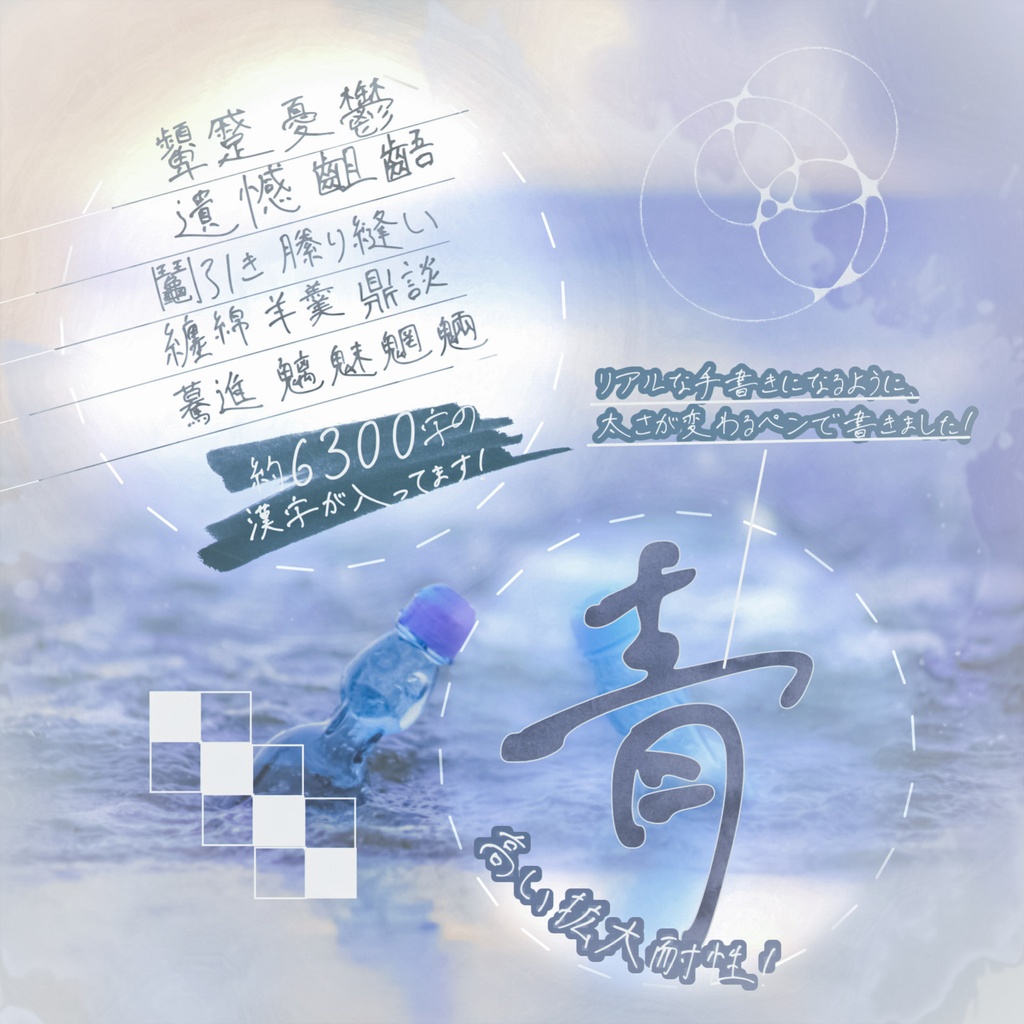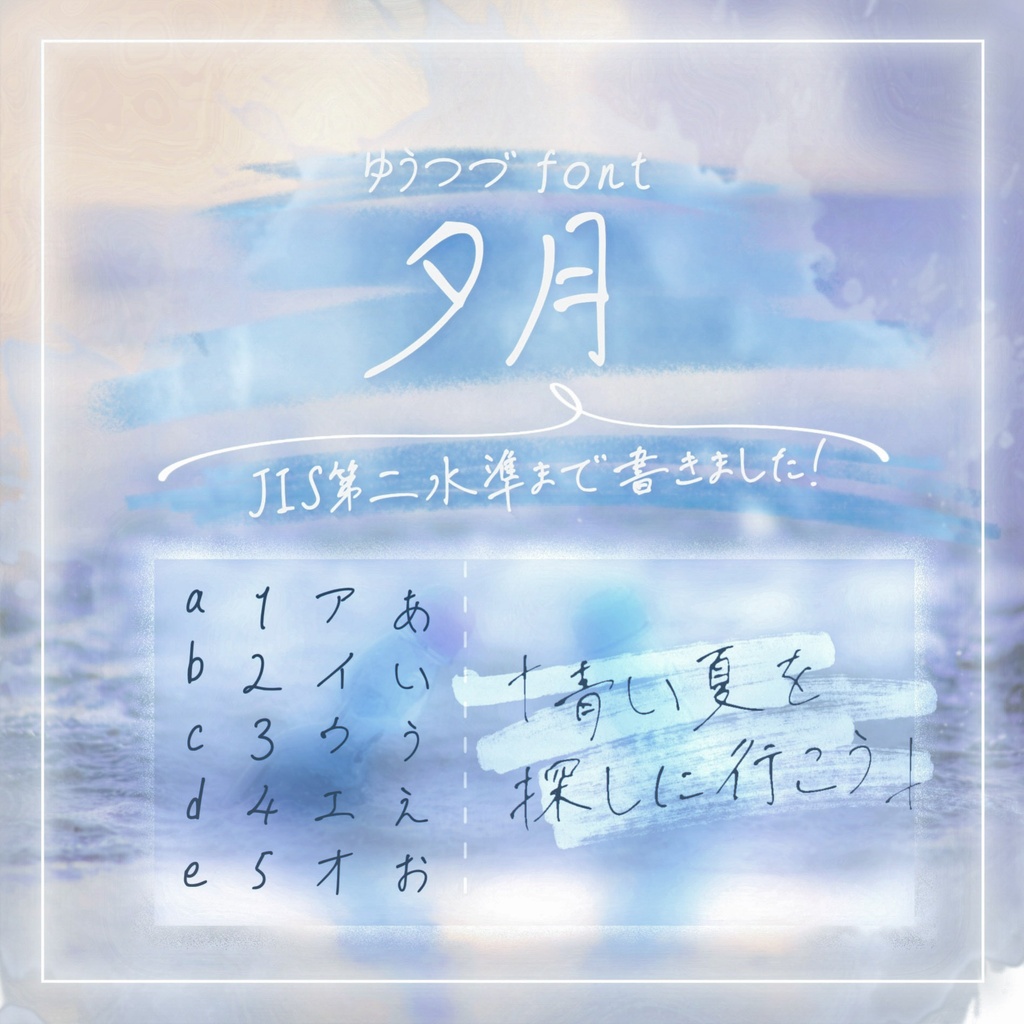
【無料版あり】手書き風日本語フォント「夕月(Yutsudu)」 oso
────────────── 🌙 1000スキ!&一周年記念 ────────────── いつも「夕月」を見つけてくださり、ありがとうございます。 おかげさまで 1000スキ!を突破しました 🎉 そして、公開から一周年を迎えることもできました。 夏の終わりに、ぜひ「夕月」をお手に取ってみてください。🌿 ■ 紹介 JIS第二水準まで対応した、爽やかで柔らかい手書き風日本語フォントです! 日常生活で用いる漢字はもちろん、難解な語句、地名にも対応しております。 縦書きにも対応しています。 人間味あふれる字形で、どこか儚く、淡く、青々しい情景と相性抜群です! 打つだけで演出できる「エモさ」を、ぜひお試しください。 ■ 特徴 ・高い拡大耐性 ・個性的でありながら、可読性を損なわない字形 ・線の太さが連続的に、かつ滑らかに変化 ・豊富な文字収録数 ・縦書きに対応 ■ ご紹介いただいたサイト ・いいフォント 様 https://goodfreefonts.com/8397/ ・フォントラボ 様 https://font-labo.com/yutsudu-font/ ・日本語フリーフォント 様 https://ffont.jp/yutsudu/ ・coliss 様 https://coliss.com/articles/freebies/japanese-free-fonts.html#h209 ■ おかげさまで 累計ダウンロード数が7000を突破しました! ご購入くださった皆さまはもちろん、SNSやブログなどで紹介してくださった皆さまにも深く感謝申し上げます。 ■ 注意・留意 ・カーニングを推奨します。 ・有料版をご購入される前に、必ず無料版での使用テストをお願いいたします。 また、「スキ」ボタンを押してくださると大変励みになります! もし気に入られましたら、ぜひとも押下のほどよろしくお願いします。 このフォントは、生成AIを使用して制作したものではありません。 作者自身が一文字ずつ手書きして制作しています。